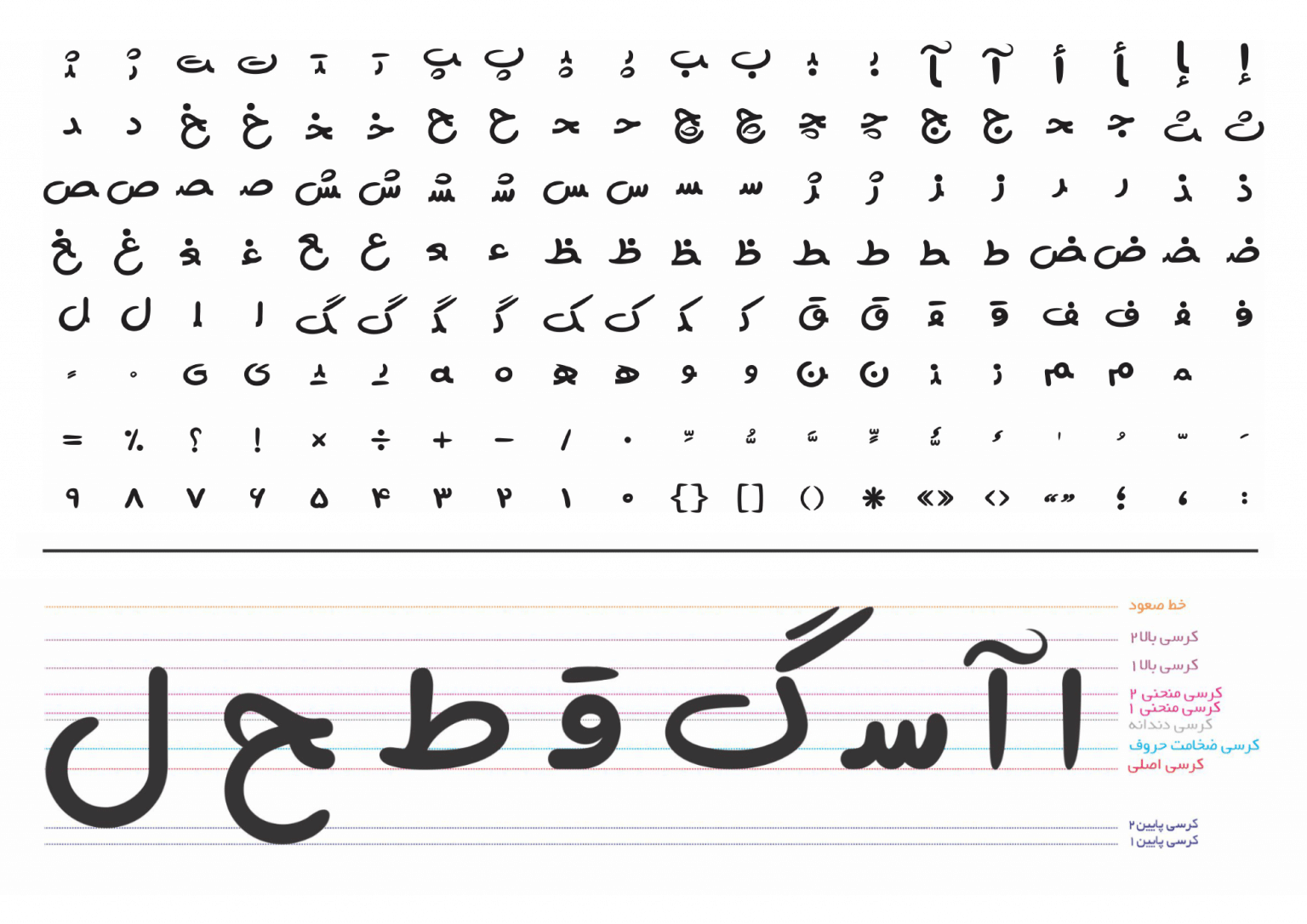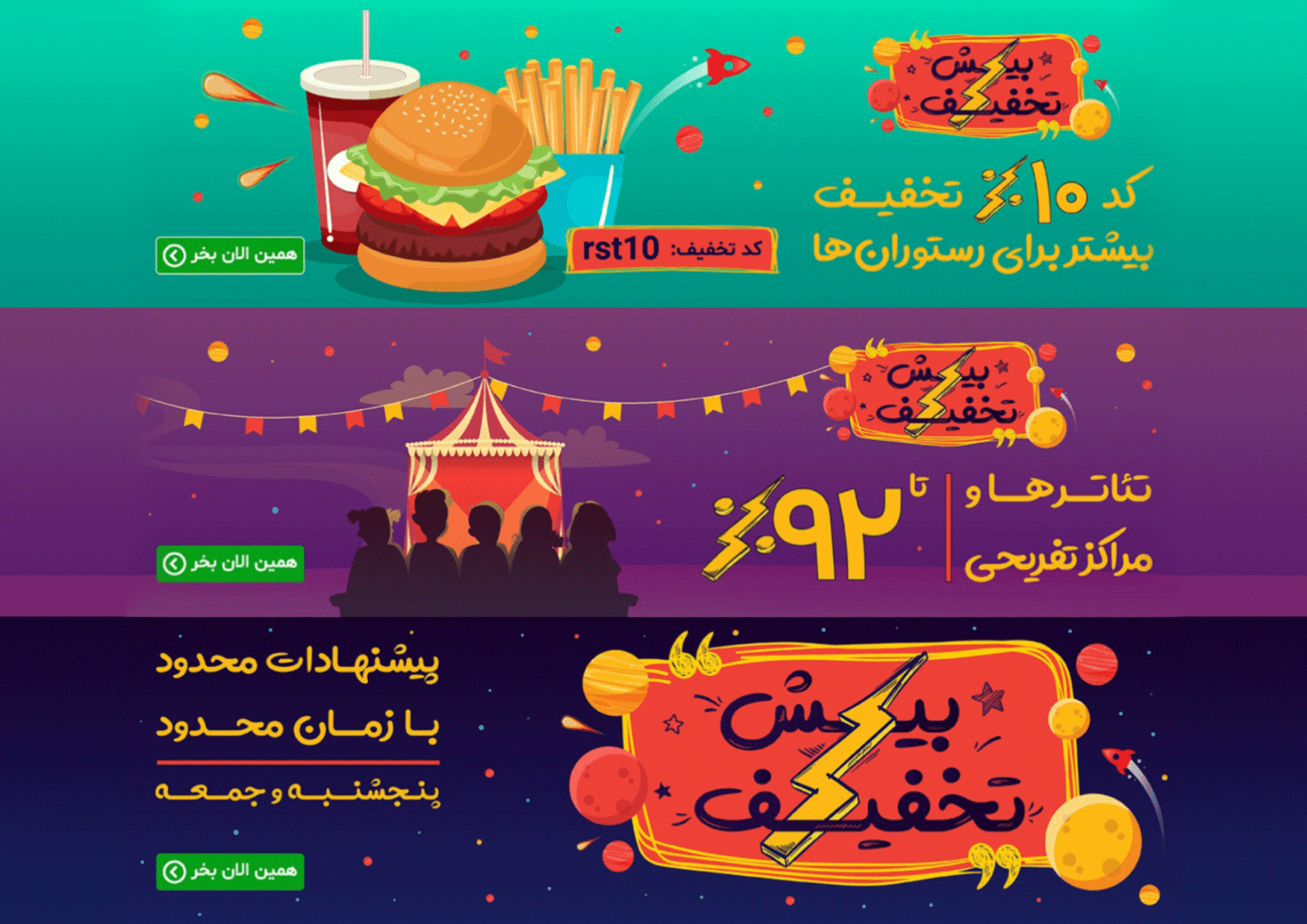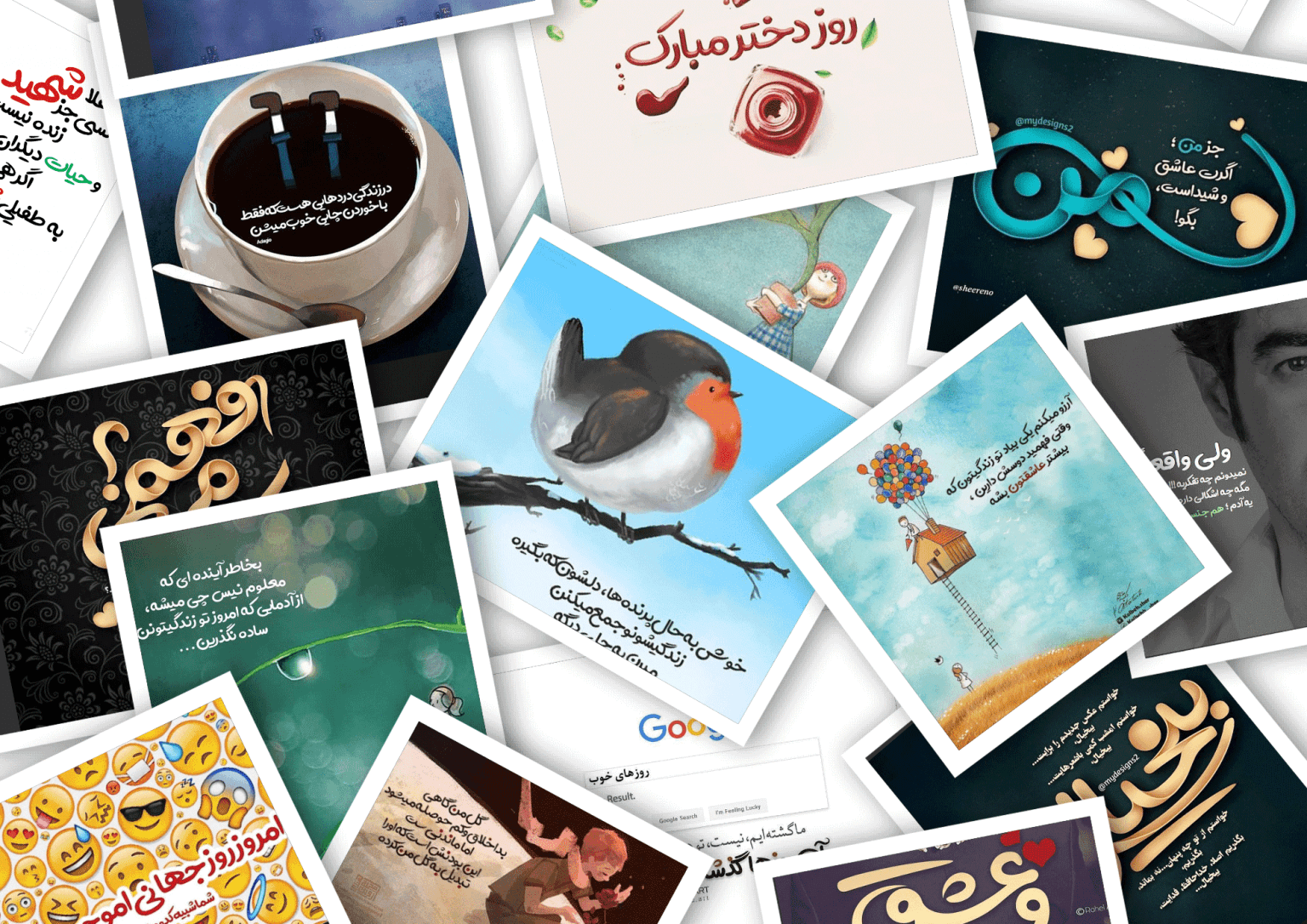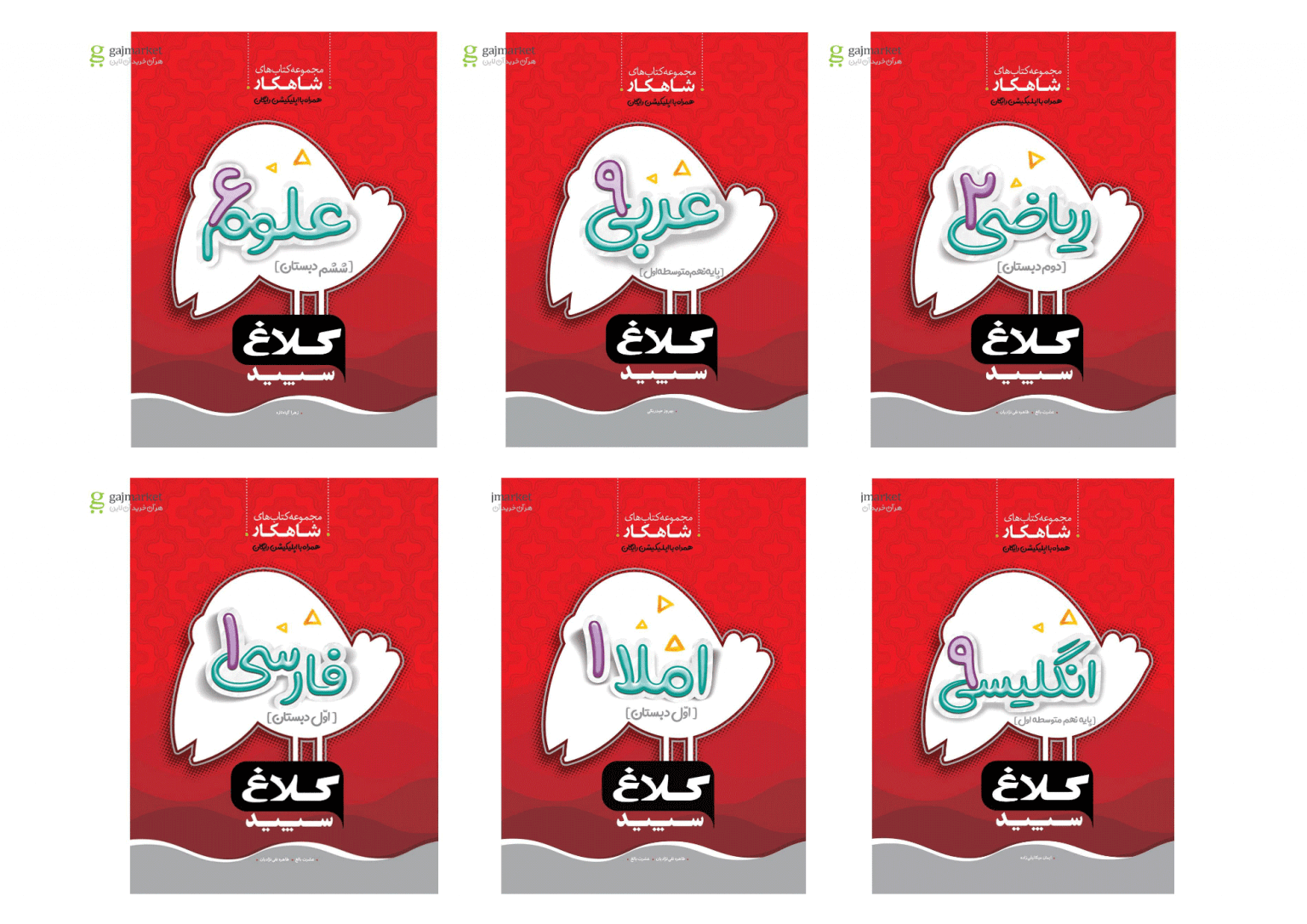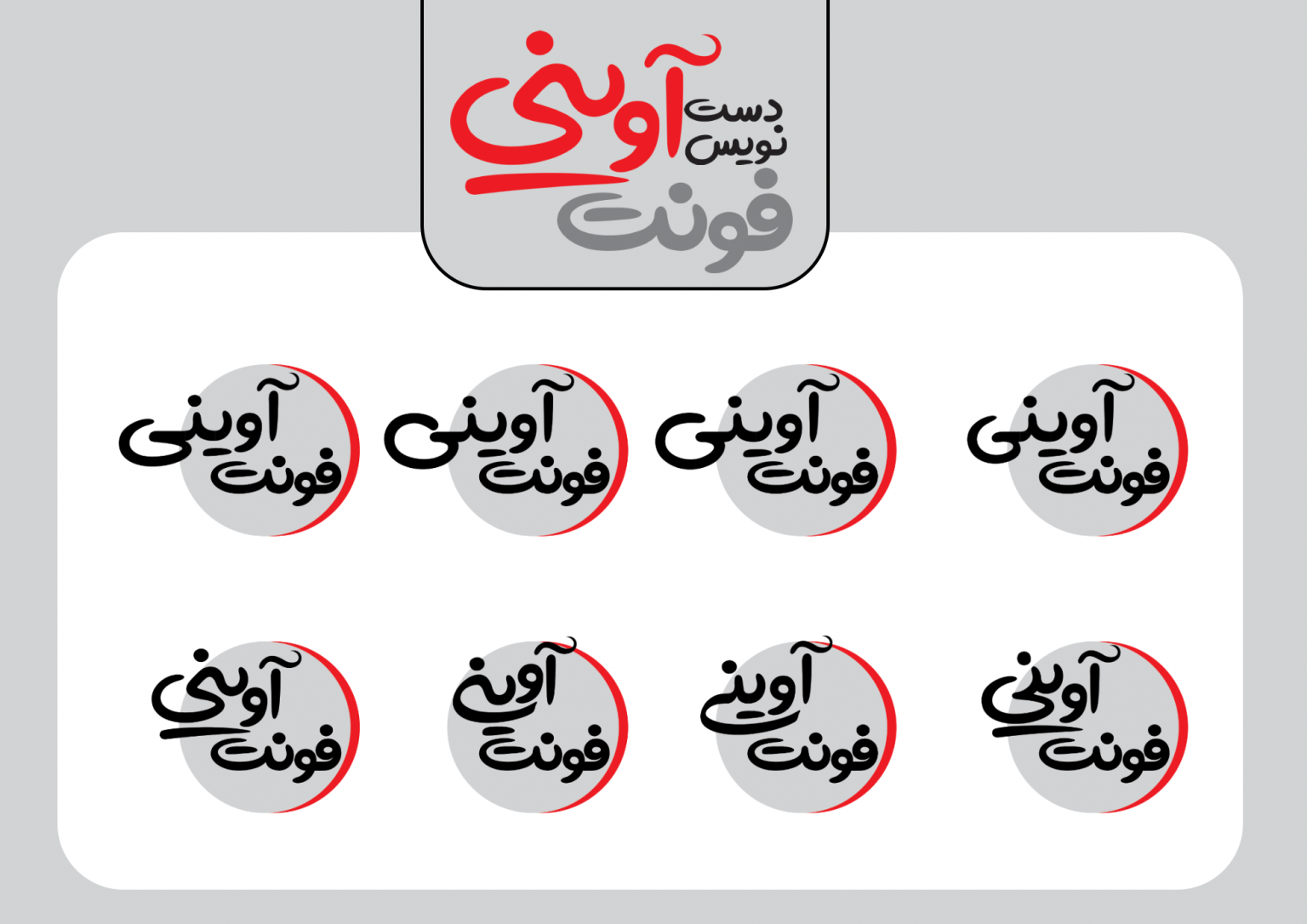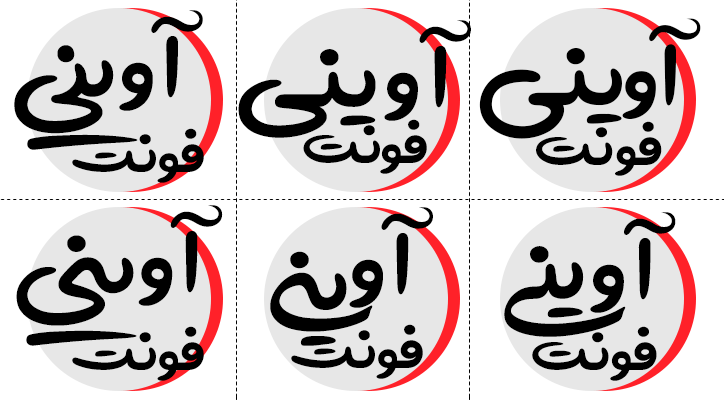
فونت آوینی یک فونت دست نویس فانتزی است که با قلمی روان و پر تحرک نوشته شده است. در اجرای نرم‌افزاری حروف سعی شده است
قابل استقاده در پوستر،لوگوتایپ،متون ساده و…
فونت آوینی یک فونت دست نویس فانتزی است که با قلمی روان و پر تحرک نوشته شده است. در اجرای نرم‌افزاری حروف سعی شده است تا حد امکان شکل حروف نرم و فاقد شکستگی باشد در نتیجه شما با فونت‌ی زیبا روبرو هستید که به راحتی حس نشاط و سرزندگی را به اثر گرافیکی شما منتقل می‌کند.
طراح فونت آوینی قاسم نجاری است که این تایپ‌فیس را برای اجرای کارهای گرافیکی خانه طراحان انقلاب اسلامی بصیر که مروج فرهنگ شهادت است طراحی کرده‌ و برای همین نام سید شهیدان اهل قلم سید مرتضی آوینی را برای این تایپ‌فیس انتخاب کرده است.
• این فونت فقط حاوی حروف فارسی و عربی و انگلیسی است.
در ادامه نمونه متن و کارهای گرافیکی اجرا شده توسط این فونت را ببینید
تایپ فیس فونت آوینی
ترکیبات متغیر و جایگزین کلمه آوینی ( فونت آوینی دارای 800 گلیف ترکیبی و جایگزین می باشد)
نمونه‌ استفاده شده از فونت آوینی در عکس نوشته
نمونه‌ استفاده شده از فونت آوینی در تبلیغات سایت فروشگاهی
نمونه‌ استفاده شده از فونت آوینی در جلد کتاب‌